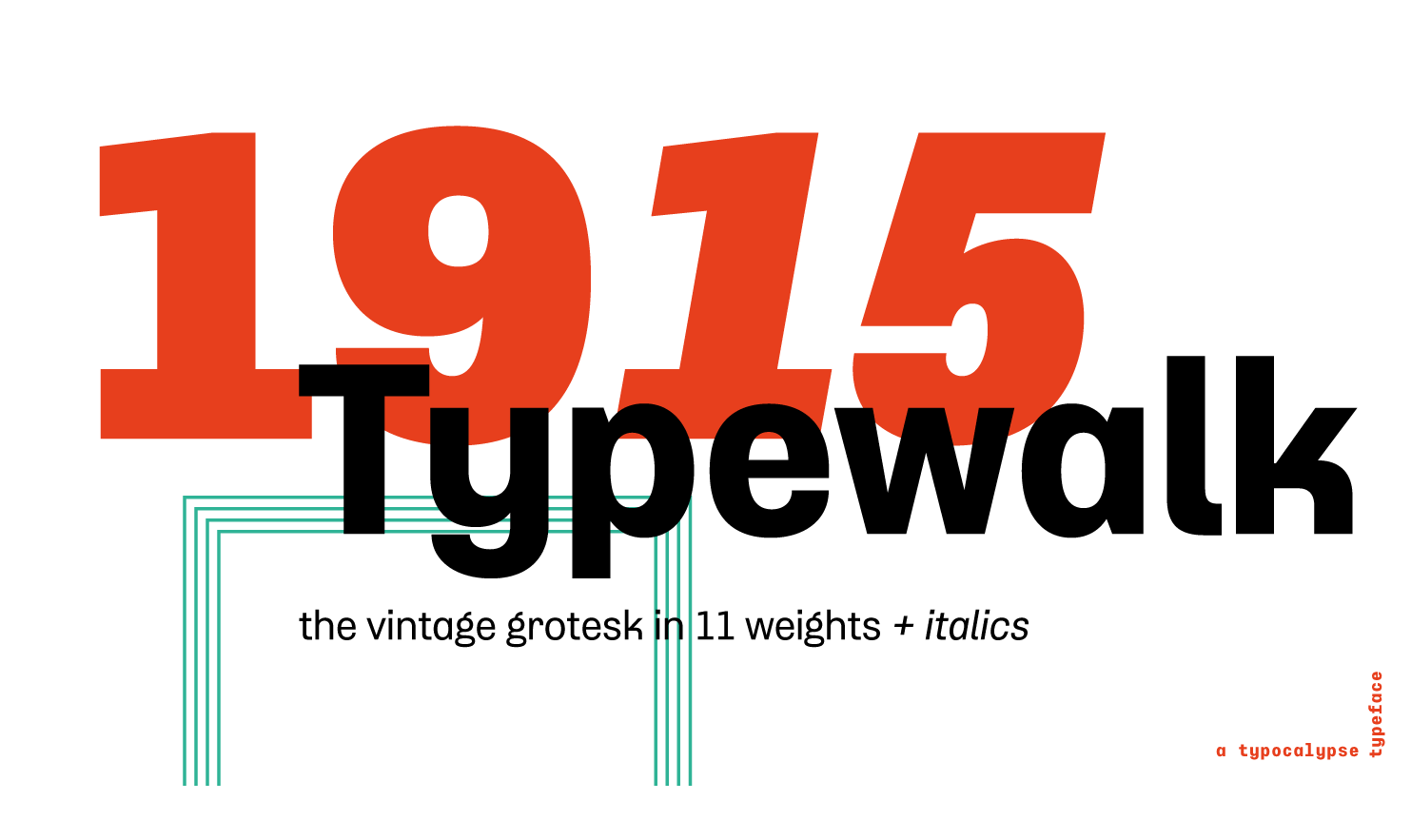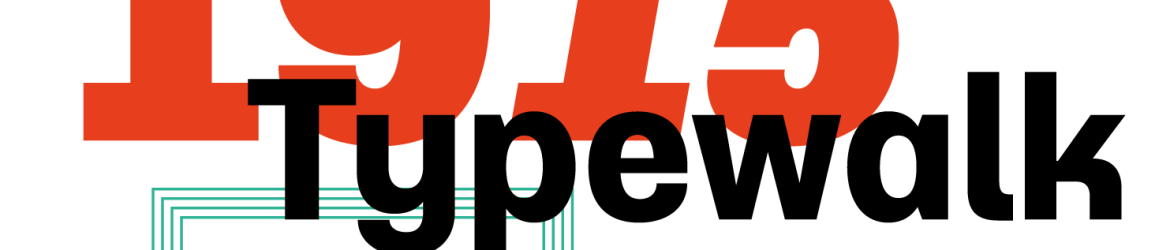
A Typewalk 1915 é uma fonte sans-serif que oferece ao designer uma paleta vibrante para trabalhos em linha e impressão. Especialmente desenvolvida por typocalypse, essa fonte lembra os traços artísticos europeus do início do século XX, enquanto honra a influência dos movimentos de objetividade gráfica da época. Inspirada nos métodos de pintura de sinais e letras desse período, ela se destaca com um toque vintage e quirk que combina elementos proto-racionais e visuais modernos. A Typewalk 1915 é uma escolha perfeita para trabalhos culturais ou editoriais, sua linguagem única fazê-la adequada para aplicativos em tela e impressão. Suas linhas curvas fluidas e a forma elegante de seus caracteres a tornam versátil e capaz de se adaptar a diversos estilos gráficos. Em um momento em que cada tipo de mídia digital busca uma identidade única, a Typewalk 1915 oferece uma conexão nostálgica com o passado artístico enquanto mantém-se atual e relevante para o futuro do design gráfico.